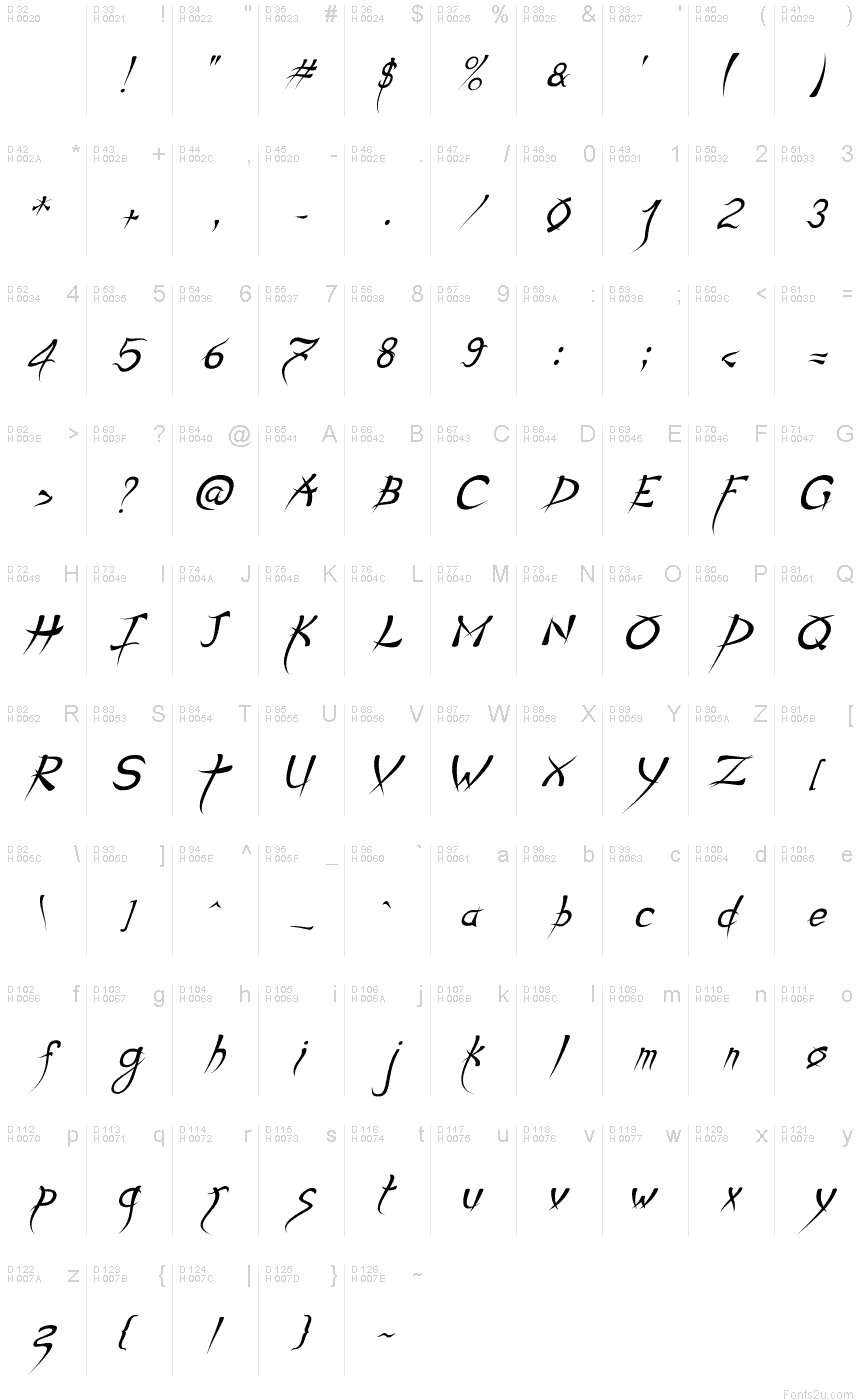
Psycho Italic 字体
Psycho Italic
Remy Demarest
由 Remy Demarest 设计的 Psycho Italic 是一款免费的恐怖风格显示字体,看起来就像是用刀刻在纸上,而不是用笔写出来的。字母带着尖锐、陡峭的倾斜度向前冲刺,细如针尖的笔画突然变粗,形成墨迹斑斑的钩子和扭曲。这种不稳定性是刻意营造的——非常适合当你想要让标题看起来疯癫、狂躁或被附身,而不仅仅是“吓人”的时候。
使用 Psycho Italic,你可以让恐怖电影海报、砍杀片标题、鬼屋品牌、密室逃脱图形、暗黑系书籍封面以及令人毛骨悚然的 YouTube 缩略图瞬间进入极致恐慌模式。这款免费字体在字号较大时效果最佳,它那锯齿般的动感和戏剧性的曲线可以大声“尖叫”。将 Psycho Italic 与一款简洁、紧凑的无衬线字体搭配用于正文,既能保持易读性,又能让 Psycho 系列字体带来最强烈的心理冲击。